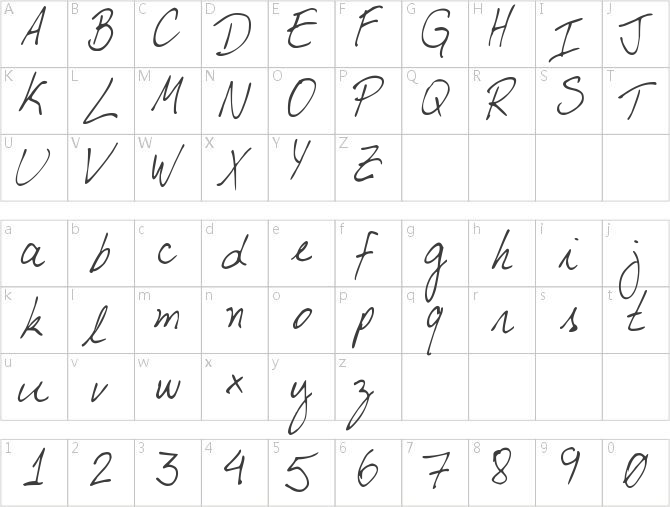
My Boyfriend's Handwriting
My Boyfriend's Handwriting介紹
My Boyfriend's Handwriting字體字庫是一款讓人賞心悅目、百看不厭的英文字體,適合各類廣告和產品包裝設計應用,字體大小0.06MB,格式為ttf字體,上傳用戶是多喝燙水,作者/版權方為未知